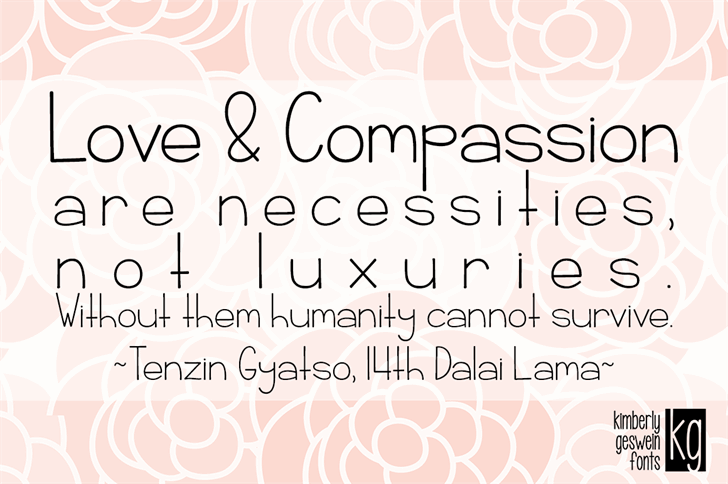
KG Rise UP Font – Download Grátis
A fonte KG Rise UP é uma escrita manuscrita que se destaca com seu toque delicado e personalizado. Seu design original e criativo está disponível para aqueles que desejam um ar de simplicidade mas com uma pitada de estilo, especialmente adequado para lembretes de compromissos importantes ou expressões emotivas em designs digitais. O designer Kimberly Geswein trouxe uma característica única: o horizontal barra vertical |||| contém um estilizado desenho de um estrela, com as palavras “RISE UP” escritas dentro dela. Este detalhe não só torna a fonte mais visualmente interessante e memorável, mas também serve como um lembrete para os usuários sobre o propósito do uso ético da sua fonte: promover uma melhor compreensão e amor no mundo. Para aqueles que estão interessados em usar essa fonte de maneira comercial, a Kimberly Geswein está disponível na página online para obtenção dos direitos autorais.
Designer: Kimberly Geswein